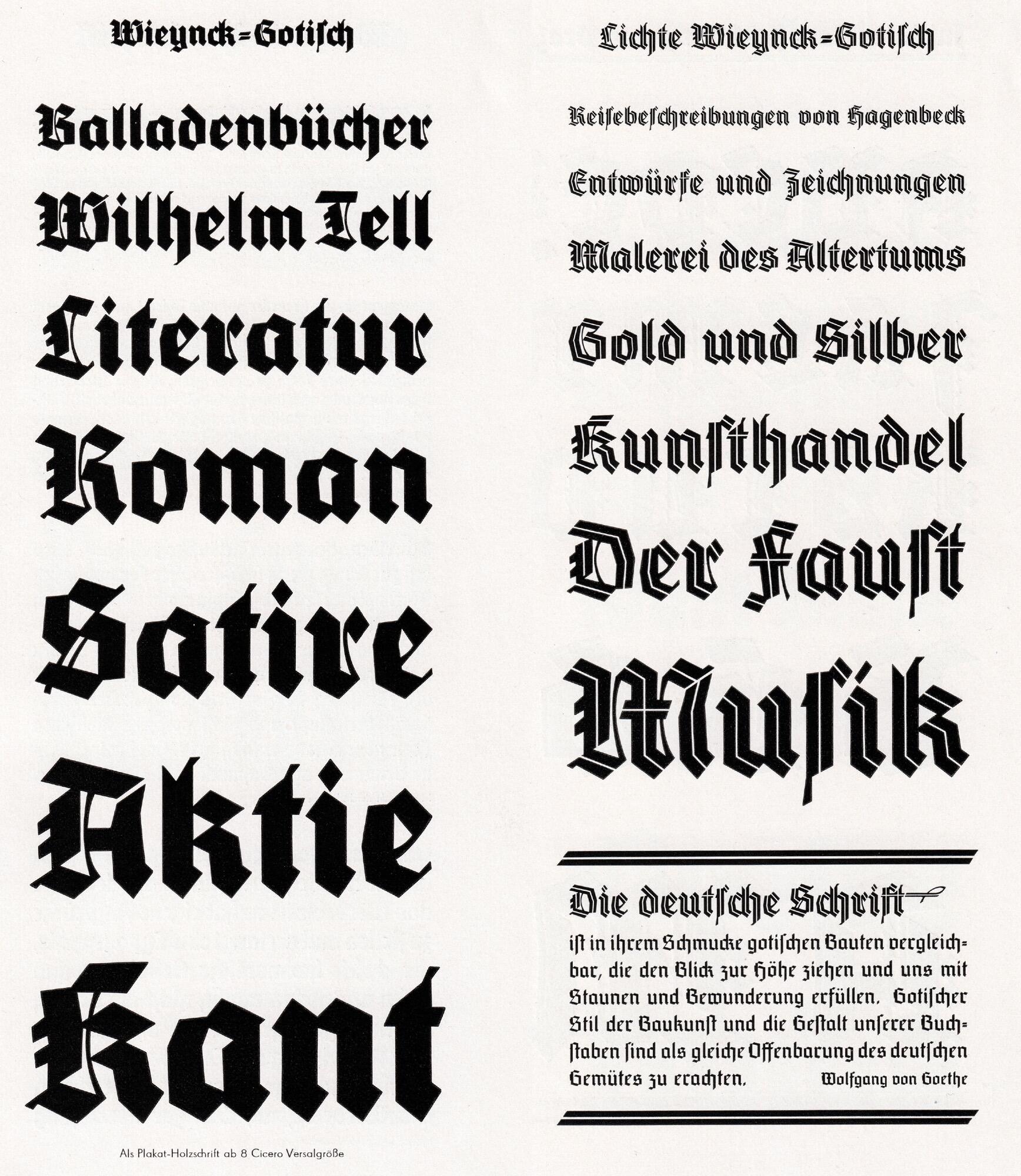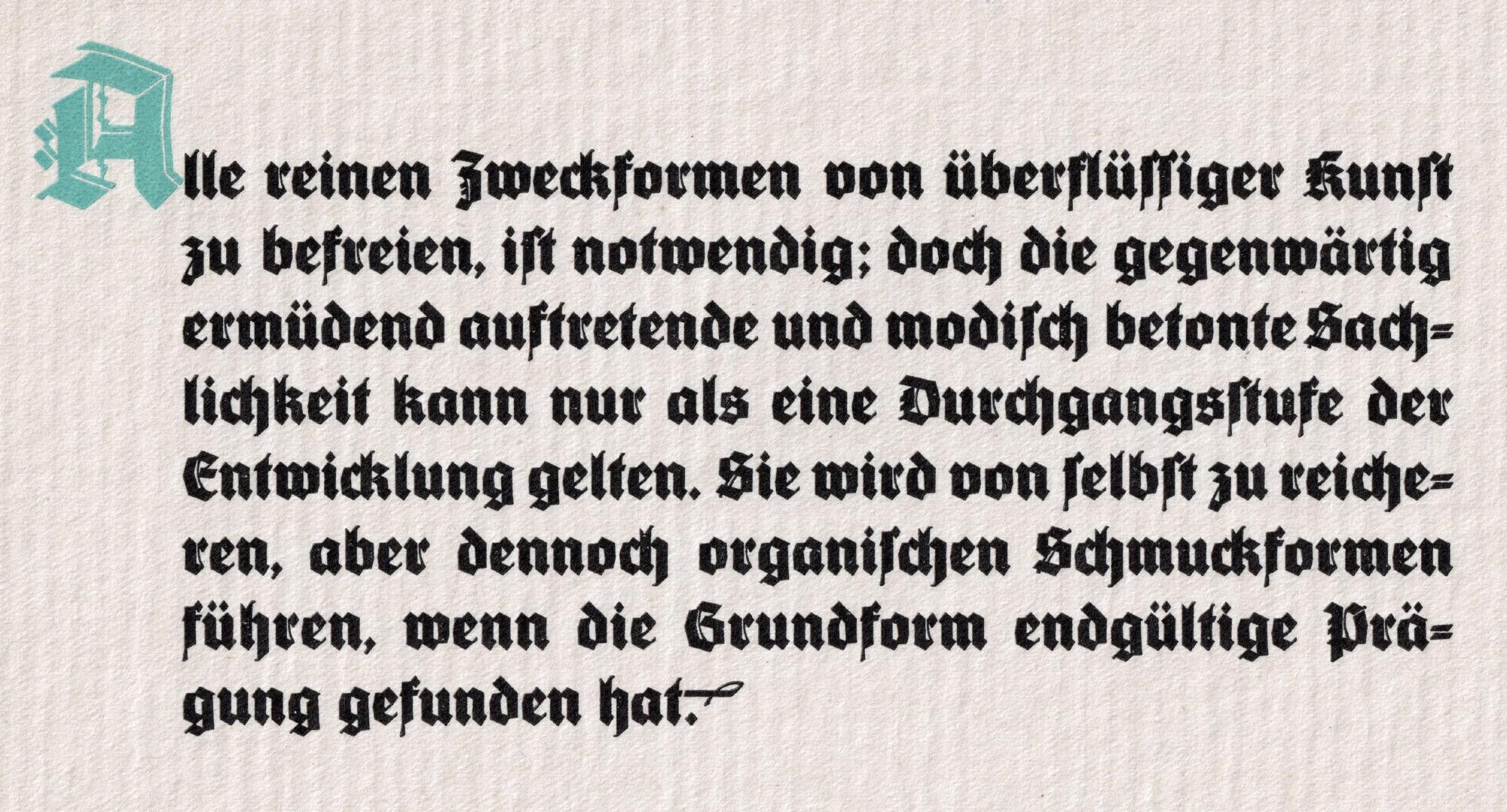
Die kräftige Wieynck-Gotisch von Heinrich Wieynck erschien ab 1926 bei der Dresdner Schriftguß AG. Eine dekorative lichte Garnitur wurde 1930 ergänzt. Eine Digitalisierung beider Schnitte wurde 2017 von RMU Fonts veröffentlicht. Die Fonts verfügen über eine westeuropäische Belegung und enthalten ein langes s und die deutschen Fraktursatz-Ligaturen.